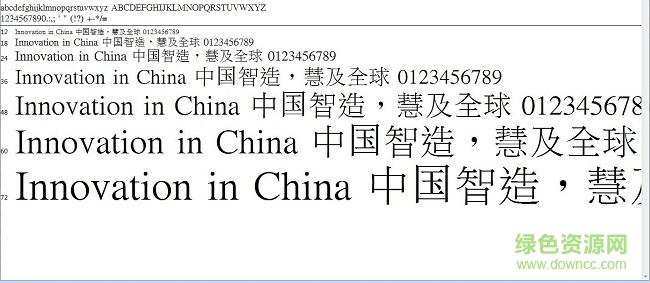
蘋果儷宋 pro
蘋果儷宋 pro字體是一款橫輕直重的宋體字體,字身秀美,大方溫和有氣質(zhì),閱讀非常便捷,常常用在PPT或書籍的用于內(nèi)文之中,需要的朋友歡迎免費(fèi)下載!
宋體字體特點(diǎn)
橫細(xì)堅(jiān)粗,“撇如刀,點(diǎn)如瓜子,捺如掃”筆劃嚴(yán)謹(jǐn),帶有裝飾性的點(diǎn)線,字形方正典雅,嚴(yán)肅大方,是美術(shù)字體之首。
蘋果儷宋 pro